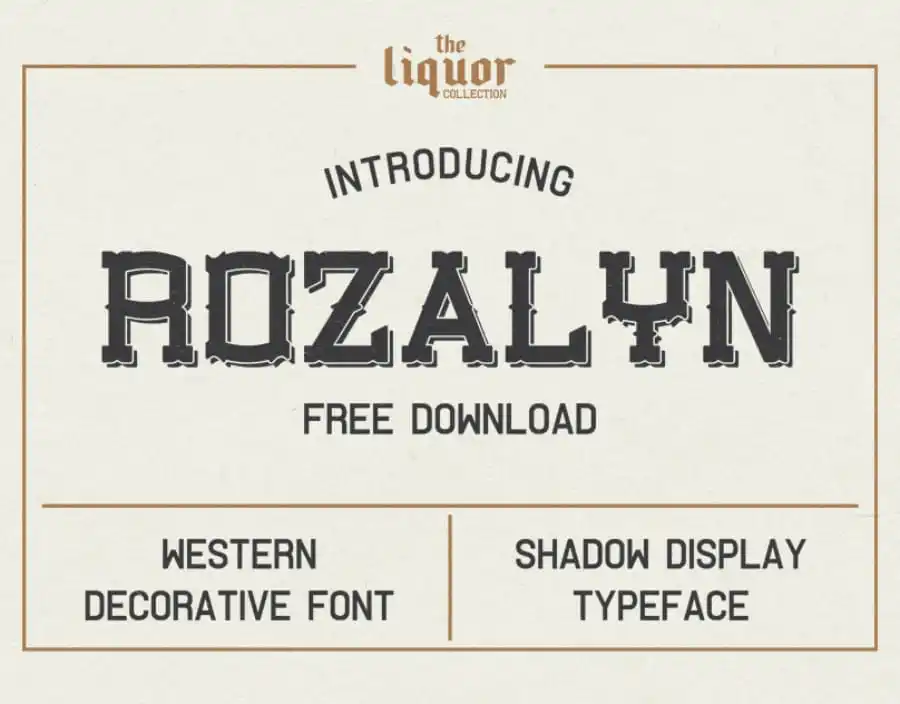
Rozalyn Shadow Typeface – Download Grátis
Introduzimos a Rozalyn Shadow Typeface! Esta elegante fonte de display foi criada por Hamilton do BART.Co Design e faz parte da coleção “The Liquor Collection”. Rozalyn é uma tipografia decorativa inspirada nos cartões de corretagem retro e anúncios dos anos 50. Uma das aplicações mais comuns desta fonte são para logotipos, etiquetas, embalagens e cartazes. Suas linhas leves e elegantes dão um toque sofisticado a qualquer design que você desejar incorporar. Ideal tanto para ambientes modernos quanto clássicos, Rozalyn é uma escolha inteligente para designers buscando uma fonte de display atraente e original. Não perca essa oportunidade de dar vida à sua identidade visual com esta bela fonte!